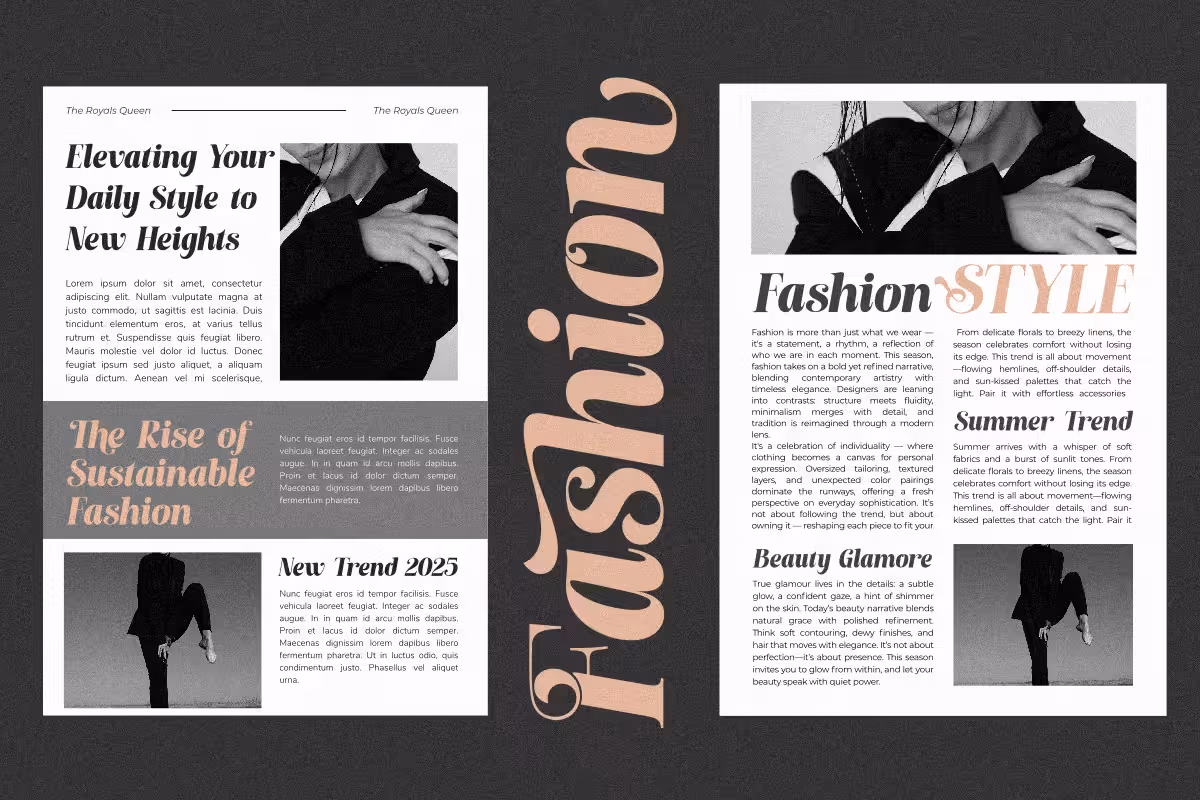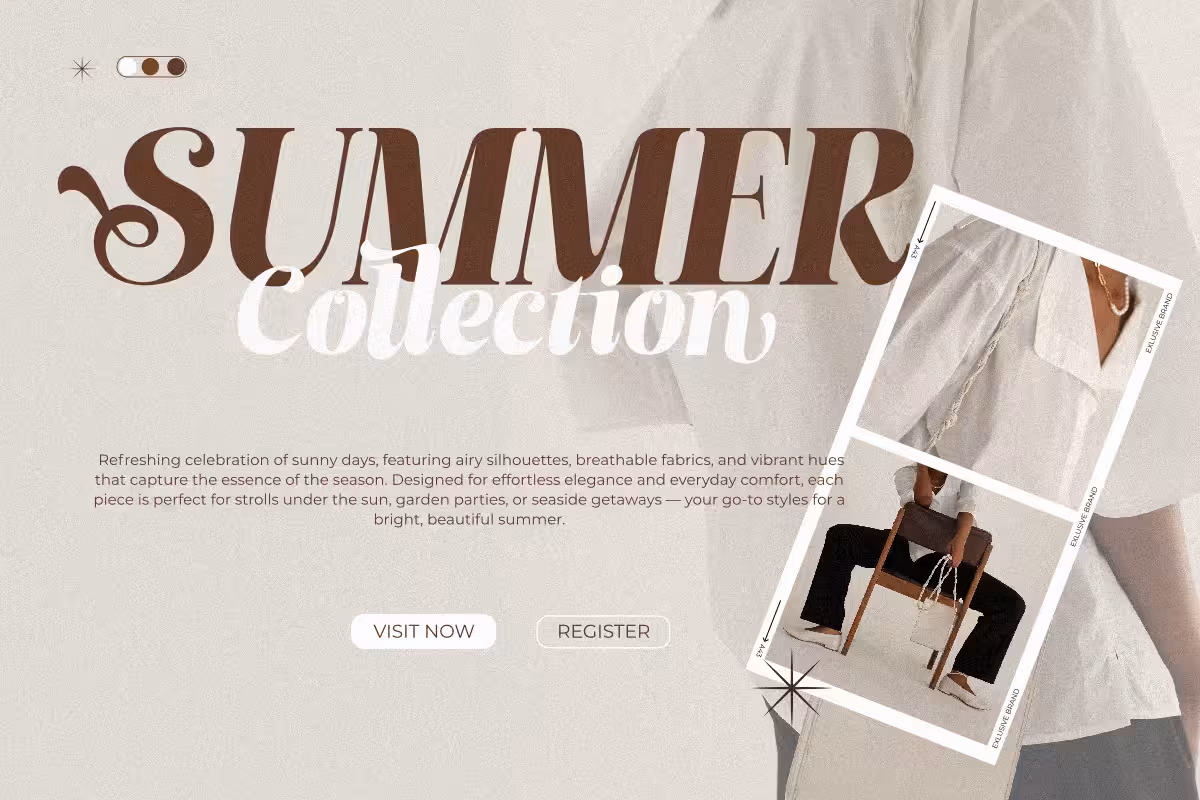
Giới thiệu về Font TF The Royals Queen Italic Việt hóa
TF The Royals Queen Italic Việt hóa là một font chữ nổi bật với thiết kế to đậm, nghiêng (italic) đầy phong thái và sang trọng, gợi nhớ đến sự vương giả và đẳng cấp. Font này toát lên vẻ đẹp kiêu sa, quyền quý và đầy lôi cuốn, lý tưởng để tạo điểm nhấn mạnh mẽ và thu hút mọi ánh nhìn trong các thiết kế đòi hỏi sự tinh tế và đẳng cấp vượt trội.
Với đặc điểm là nét chữ to đậm, dáng nghiêng quyến rũ và phong thái sang trọng, The Royals Queen Italic là lựa chọn hoàn hảo cho các ấn phẩm trong lĩnh vực thời trang và xuất bản cao cấp:
- Thiết kế thời trang: Hoàn hảo cho các thương hiệu thời trang cao cấp, từ logo, nhãn mác sản phẩm, đến các chiến dịch quảng bá bộ sưu tập. Font này giúp truyền tải vẻ đẹp thanh lịch, đẳng cấp và độc đáo của trang phục, nâng tầm giá trị thương hiệu. Đặc biệt, dáng nghiêng của font tạo cảm giác bay bổng và uyển chuyển, rất phù hợp với sự mềm mại của vải vóc.
- Tạp chí thời trang: Lý tưởng để sử dụng cho các tiêu đề chính, lời dẫn, hoặc các bài viết quan trọng trong các tạp chí thời trang, làm đẹp, hoặc phong cách sống. Nét chữ to đậm, nghiêng tạo hiệu ứng thị giác mạnh mẽ, làm cho nội dung trở nên sống động, gần gũi và thu hút độc giả, đồng thời khẳng định sự tinh tế của tạp chí.
- Thiết kế nước hoa và mỹ phẩm cao cấp: Phù hợp cho bao bì, nhãn hiệu hoặc các ấn phẩm quảng cáo muốn truyền tải sự quyến rũ, sang trọng và độc quyền.
- Thiết kế sự kiện và ấn phẩm hạng sang: Tuyệt vời cho các thiệp mời sự kiện VIP, menu nhà hàng sang trọng, hoặc các tài liệu quảng cáo cần tạo ấn tượng về sự độc quyền và đẳng cấp.
Với TF The Royals Queen Italic Việt hóa, bạn có thể dễ dàng thổi hồn vương giả, sự tinh tế và vẻ đẹp hoàn hảo vào các thiết kế, tạo ra những sản phẩm không chỉ đẹp mắt mà còn đầy cảm xúc và sức hút đặc biệt.
Font Việt hóa TF The Royals Queen Italic